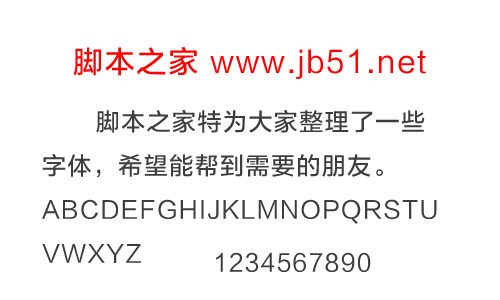
方正蘭亭準黑_GBK字體(fzlthunhk--gbk1-0.ttf)是由方正字庫推出的一款中文黑體字體,該字體是方正蘭亭黑的特別優(yōu)化版,目的是為了適應(yīng)便攜式屏幕的用字需求。針對屏幕閱讀版面每行字數(shù)少、手持視距較短、屏幕像素密度高等特性,可以應(yīng)用于文本裝潢、信息展示、頁設(shè)計、篆刻制模、數(shù)據(jù)制作、裝潢設(shè)計、計算藝術(shù)設(shè)計、視覺設(shè)計、字帖等一切合法應(yīng)用場景,支持android、Windows、Mac等系統(tǒng)安裝使用,歡迎需要的朋友前來下載。